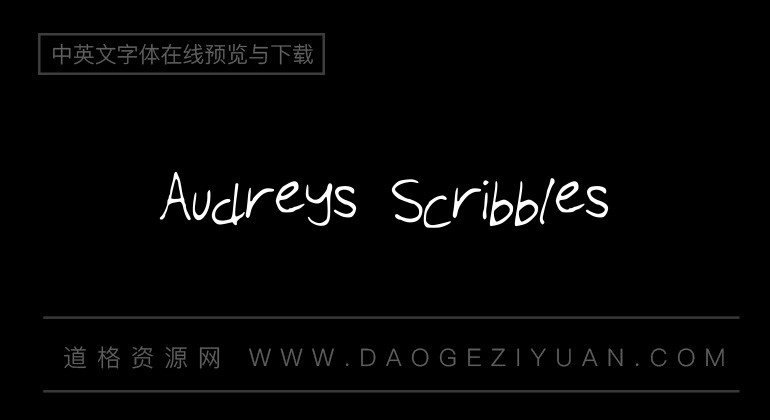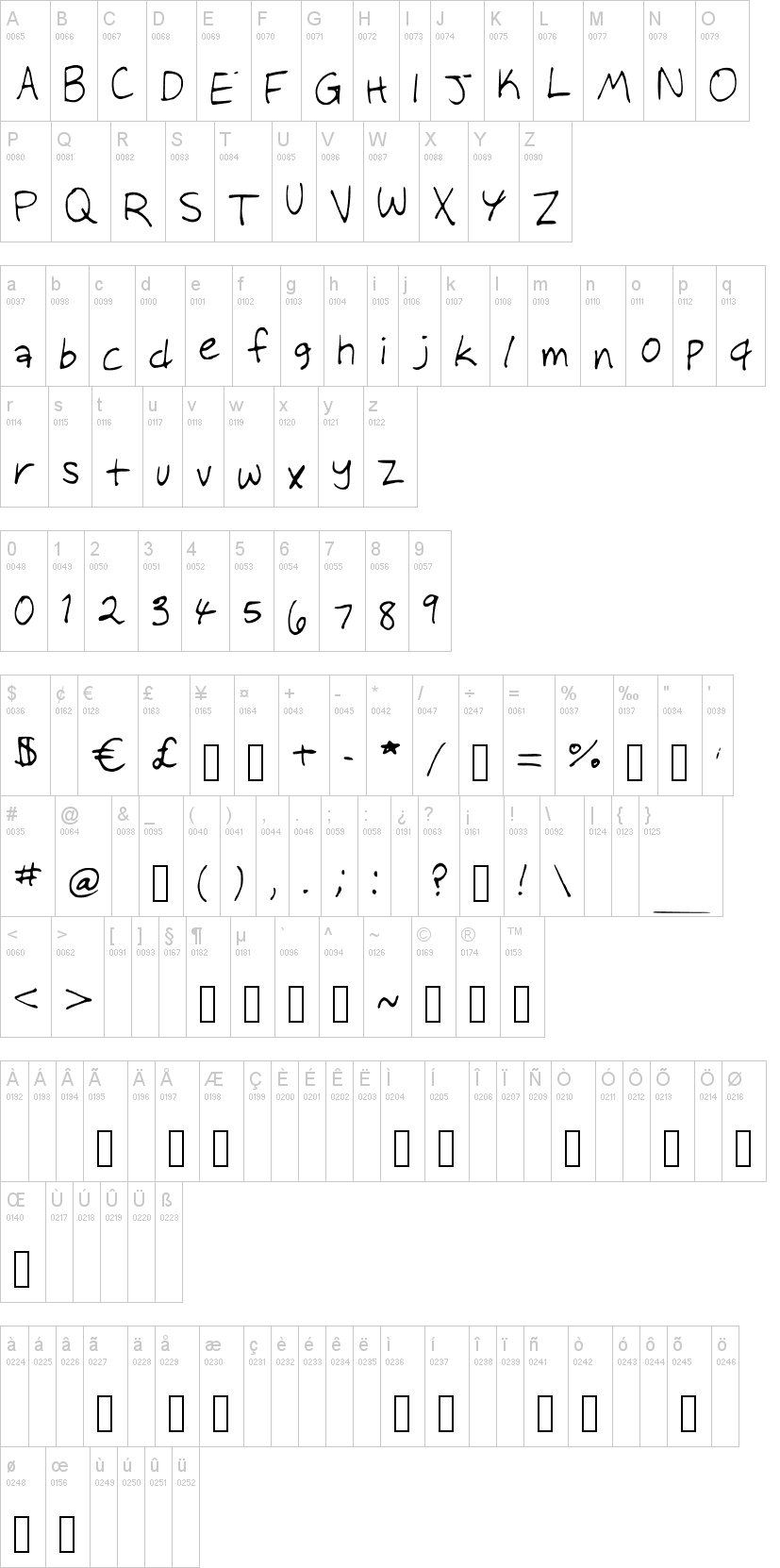
Audreys Scribbles 是一款由 Audrey 创作的手写字体,它具有温和、细腻、柔和的特点,适合用于卡片、拼贴画、海报、T恤等等各种设计项目,它拥有大量的细节,可以帮助您创造出独特的设计。Audreys Scribbles 字体拥有多种不同的字体风格,可以满足不同的设计需求,它可以帮助您把您的想法变成现实,以完美的方式呈现您的作品。内容介绍
Audreys Scribbles是一款非常不错的手写艺术字体,具有很好的视觉感,适合于文化类的宣传设计、商业类品牌的广告和产品包装设计以及个性化文字排版等较多场景。